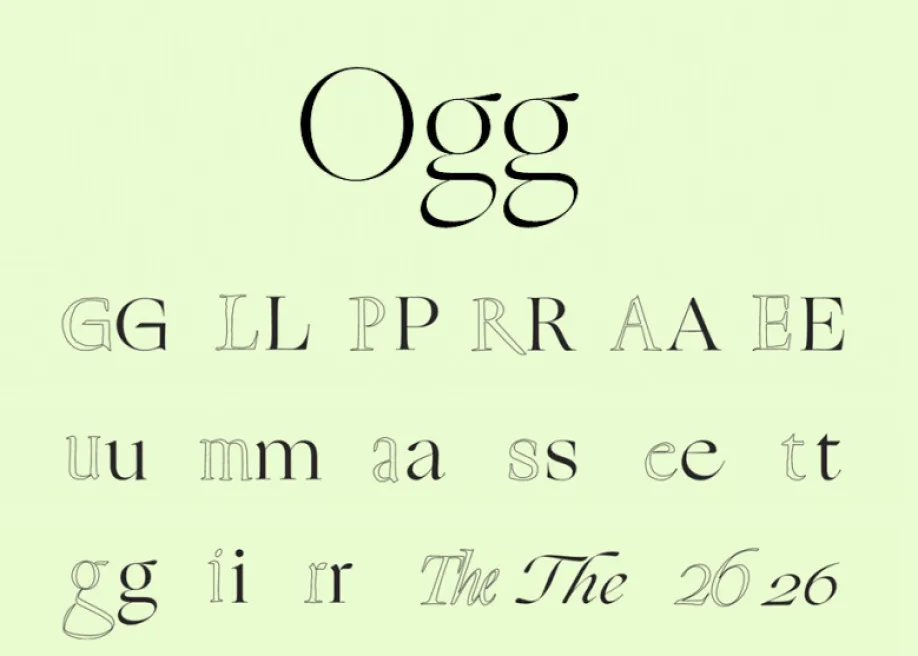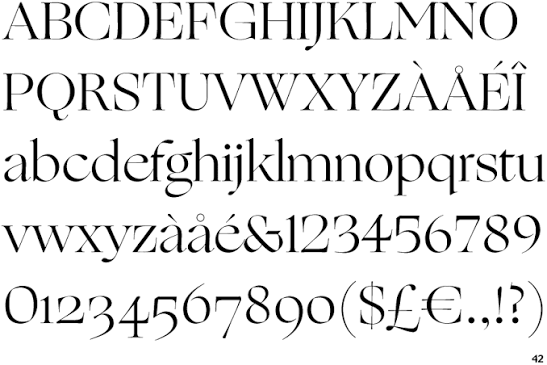
Ogg Font Việt hóa là bộ phông chữ thuộc dòng Display Serif vô cùng độc đáo, được sáng tạo bởi nhà thiết kế Lucas Sharp (Sharp Type) lấy cảm hứng từ các tác phẩm thư pháp và chữ khắc tay của nhà thiết kế sách huyền thoại Oscar Ogg. Với sự kết hợp tài tình giữa cấu trúc thư pháp bút lông mềm mại và chân chữ Serif hình học sắc sảo, Ogg mang lại diện mạo lãng mạn, trí tuệ và vô cùng sang trọng. Doozypack.vn cung cấp link tải Ogg Font Việt hóa Free chuẩn kỹ thuật, giúp bạn sở hữu phông chữ đẳng cấp này, hỗ trợ đầy đủ tiếng Việt để tự tin thiết kế bao bì và bộ nhận diện thương hiệu chuyên nghiệp.
Đặc điểm thẩm mỹ độc đáo của bộ font Ogg
Ogg không đi theo sự khuôn mẫu của các phông chữ truyền thống; nó mang đến một ngôn ngữ thị giác đầy tính biểu cảm, tái hiện trọn vẹn sự uyển chuyển của nghệ thuật viết tay dưới góc nhìn của xuất bản phẩm cao cấp.
Phong cách Calligraphic Serif lấy cảm hứng từ Oscar Ogg
Đặc trưng lớn nhất của Font Ogg là cấu trúc chữ có sự pha trộn giữa thư pháp (Calligraphy) và Serif chuyển tiếp. Các ký tự sở hữu những đường cong uốn lượn rất tự nhiên ở phần đuôi chữ, kết hợp cùng các chân chữ sắc lẹm tạo nên một nhịp điệu Typography vô cùng lôi cuốn. Khi đặt Ogg làm tiêu đề trên bao bì, sản phẩm của bạn sẽ ngay lập tức toát lên vẻ ngoài trí thức, lãng mạn và mang đậm dấu ấn nghệ thuật thủ công.
Đường nét uốn lượn uyển chuyển và độ tương phản tuyệt mỹ
Cấu trúc chữ của Ogg Font Việt hóa có độ tương phản nét thanh đậm rất cao, các nét dọc dày dặn tạo sự vững chãi trong khi các nét ngang lại thanh mảnh như sợi tơ. Tỷ lệ này giúp các tiêu đề bản thiết kế giữ được sự thanh thoát, kiêu kỳ, rất phù hợp với các mẫu hộp giấy định vị ở phân khúc thượng lưu.
Ưu điểm nổi bật của bản Ogg Font Việt hóa Free
Khi ứng dụng các phông chữ nghệ thuật quốc tế vào thị trường trong nước, sự chỉn chu về dấu câu là yếu tố quyết định đến tính chuyên nghiệp của ấn phẩm:
- Khắc phục triệt để lỗi dấu tiếng Việt: Phiên bản Việt hóa đã được đội ngũ thiết kế trau chuốt thủ công từng dấu câu. Các dấu sắc, huyền, hỏi, ngã, nặng được vẽ với tỷ lệ cân đối, đặt ở vị trí thoáng đãng so với thân chữ, không gây cảm giác chắp vá hay làm biến dạng cấu trúc thư pháp.